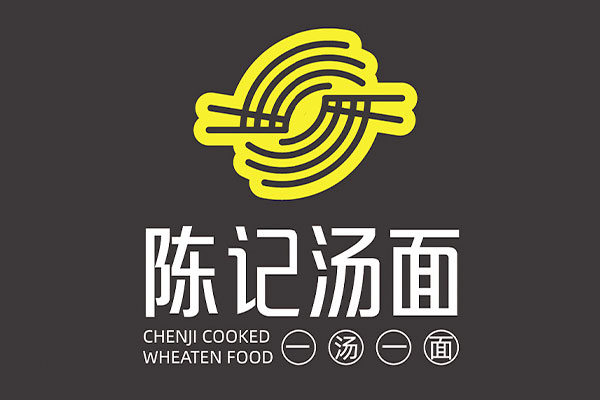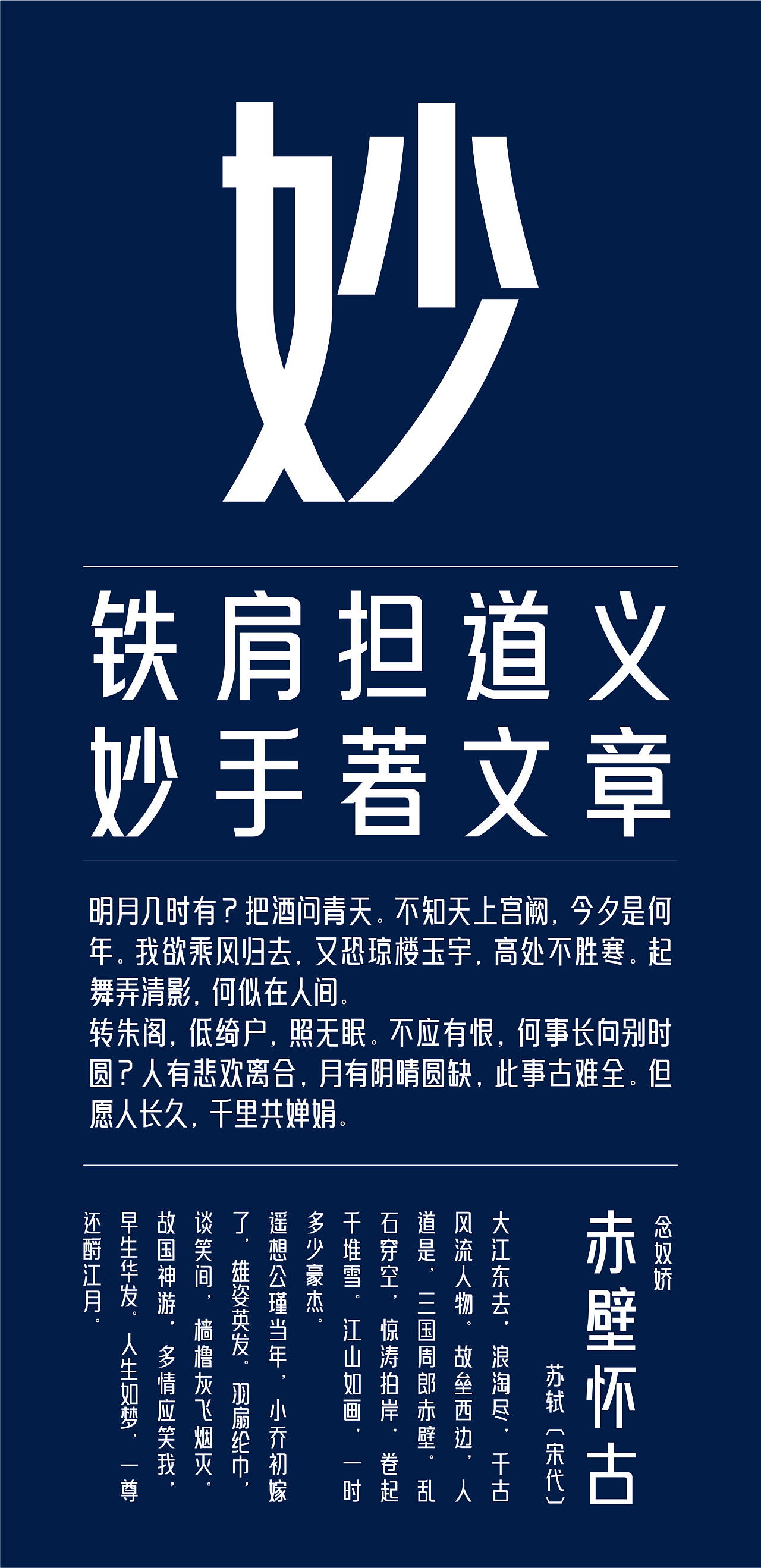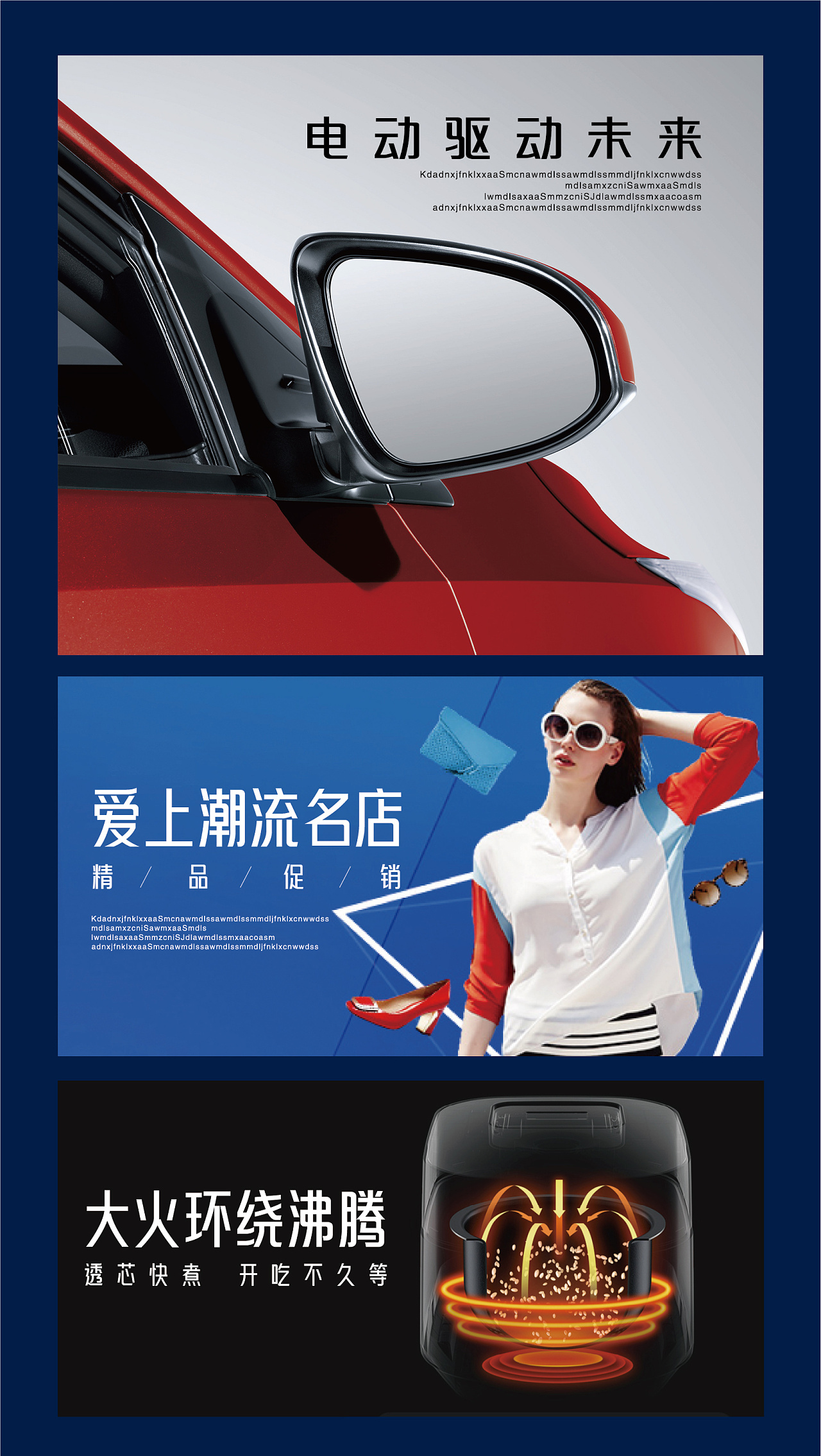
仓迹高德国妙黑
仓迹高德国妙黑是南京的高德国设计(仓迹字库)推出的一款免费商用字体,首次亮相于站酷。据作者高德国介绍,这款字体源于他数年前参加比赛的样稿,耗时一年多才得以完成。他曾与字体厂商进行过商谈,但由于价格问题未能达成合作。于是,高德国决定自行开发这款充满时尚感的字体。在开发过程中,他不断进行修改,以避免与已有的黑体风格相撞。如今,这款字体终于与大家见面了。
高德国妙黑体具有高挑时尚的特点,适合用于品牌设计、广告标题等场合。其独特的高挑结构使字体在商业创意设计中能够更好地与创意相结合,为设计师提供更好的服务。这款字体在各个行业和众多场景中都有着出色的表现。
高德国妙黑体包含7155个字形,已经覆盖了国标规定的6763个字。作者采用免费商用方式授权,大家可以放心使用!